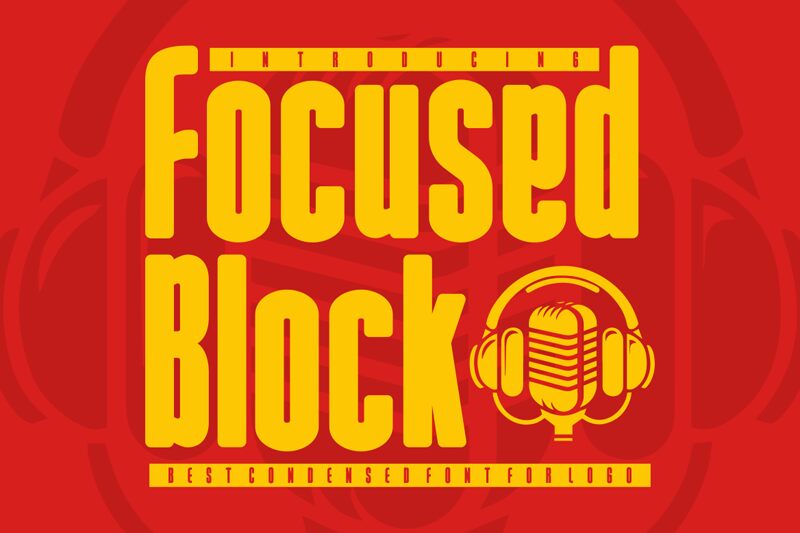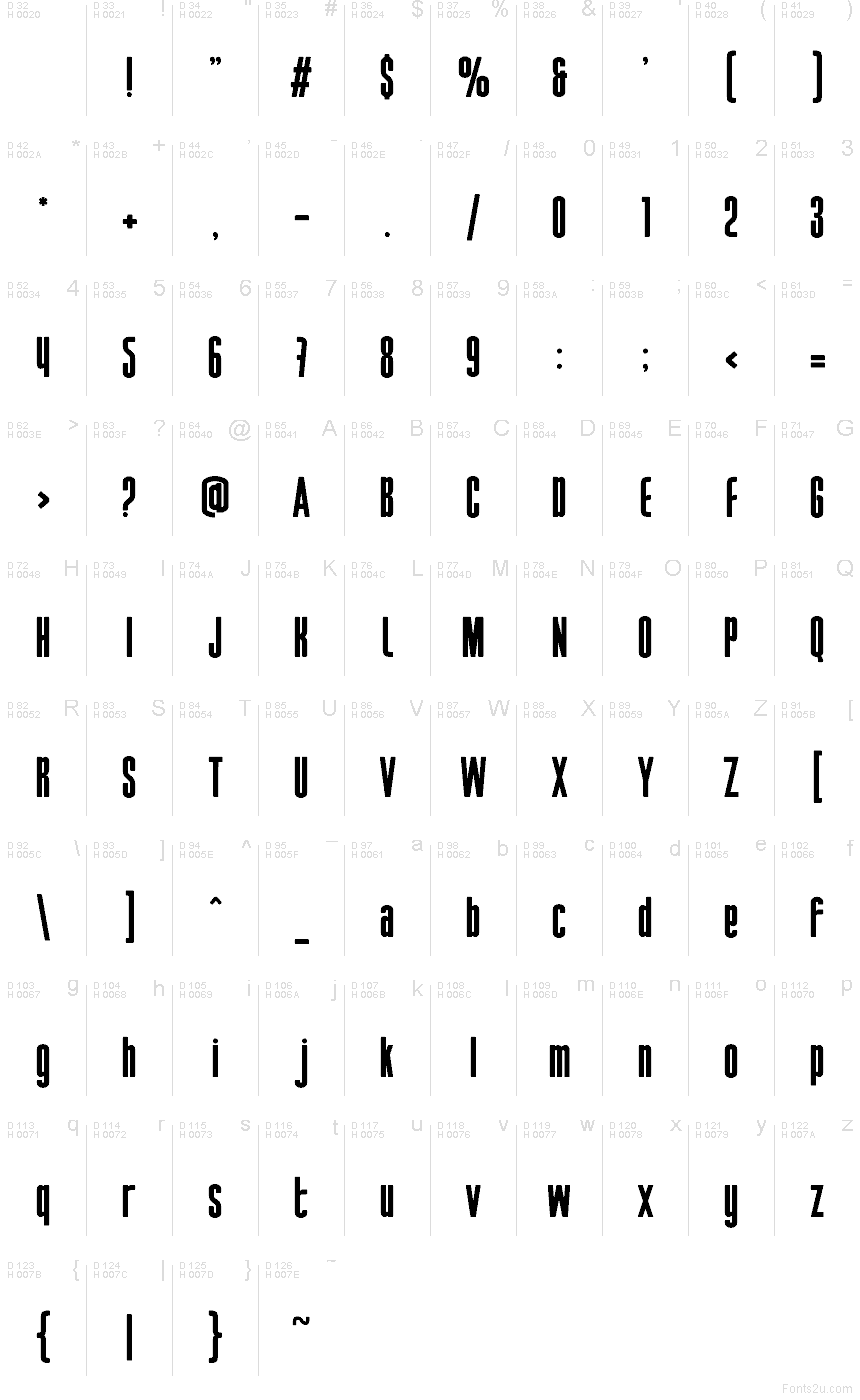
Focused Block
Focused Block od Shanaf Studio je bezplatné zaoblené a zúžené bezpätkové písmo s úderným, plagátovým rytmom. Písmená sú vysoké a husto poskladané, s hrubými ťahmi, štvorcovými krivkami a zmäkčenými rohmi, čo dáva abecede kompaktný, až modulárny vzhľad bez toho, aby pôsobila chladne.
Hodí sa pre branding, hudobné letáky, nadpisy aplikácií, obaly a výraznú sociálnu grafiku, kde tento bezplatný font skvele vynikne v krátkych, husto vysádzaných slovách. Použite ho pre titulky, obálky a úderné logotypy, ak hľadáte zúžené písmo, ktoré pôsobí mäkko, a pritom výrazne.